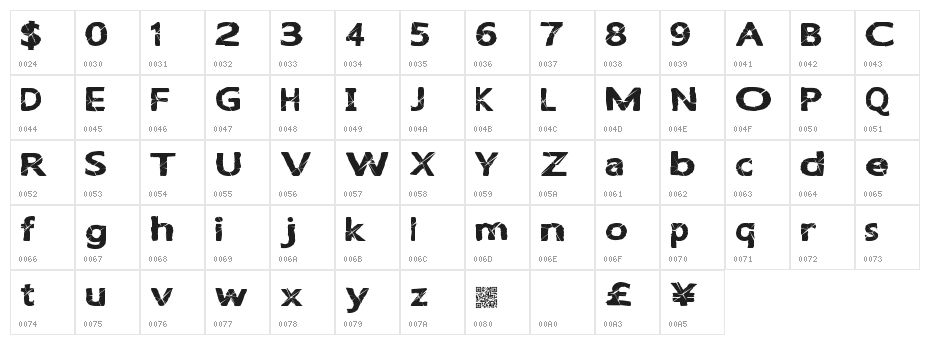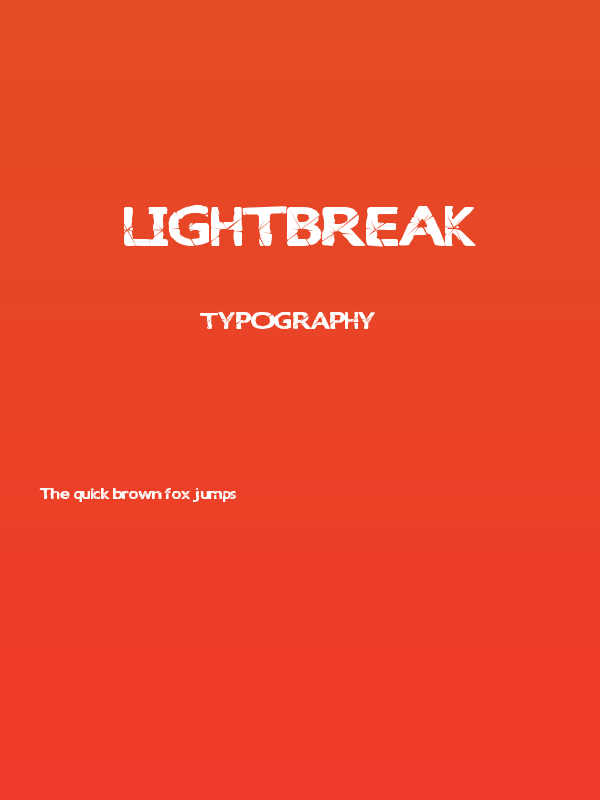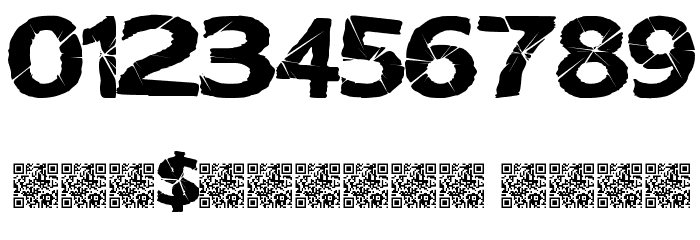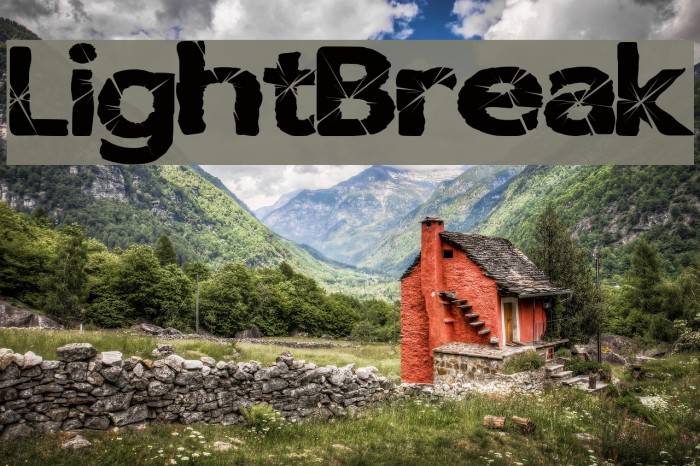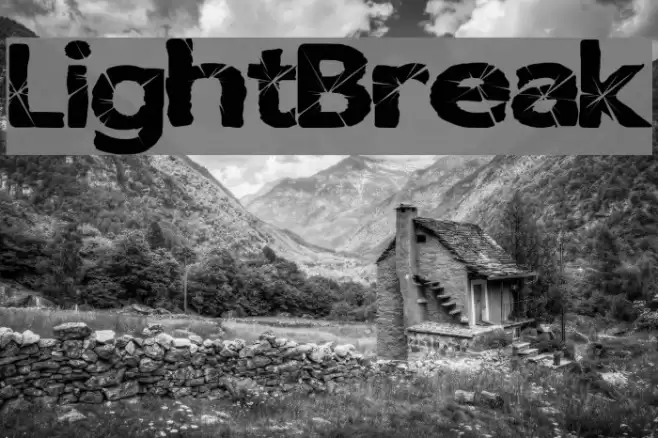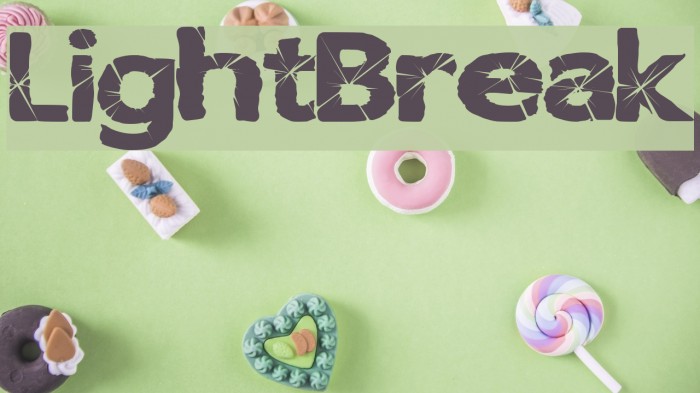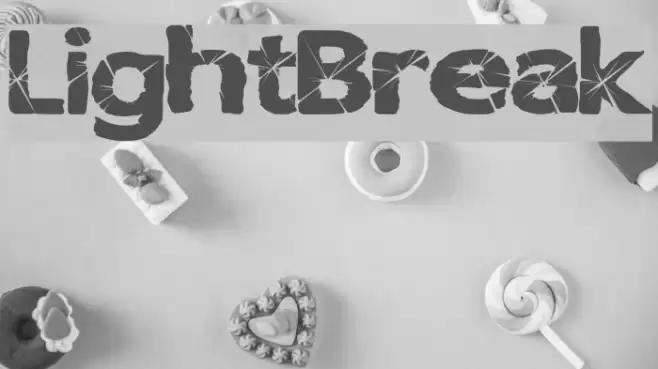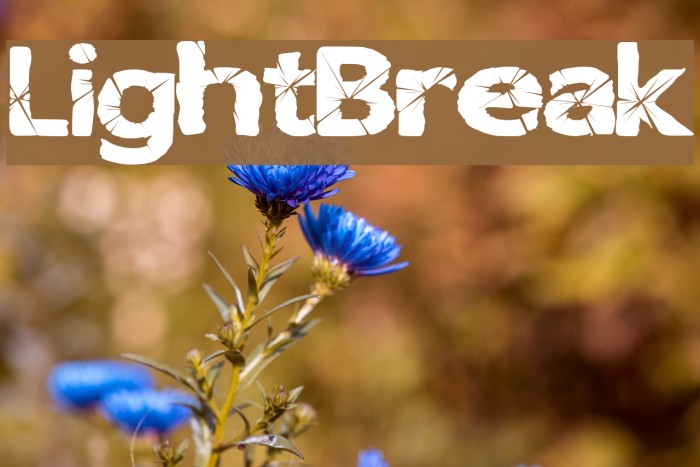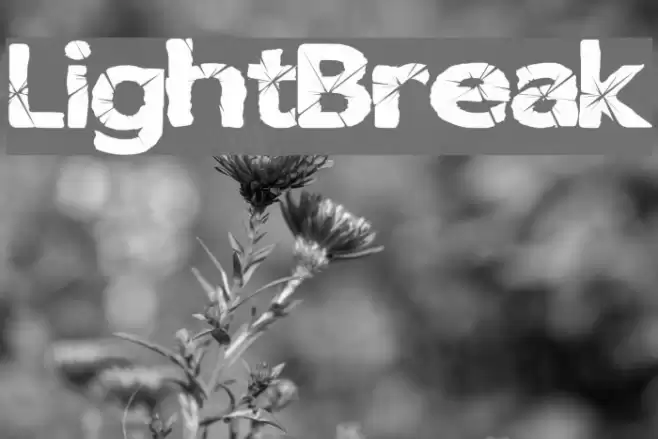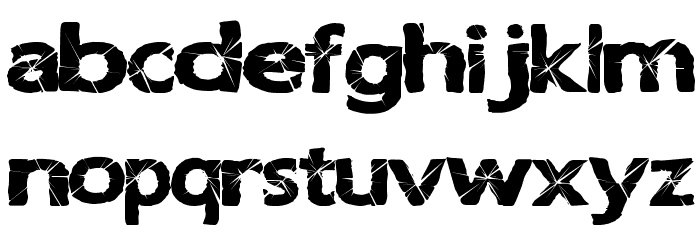
LightBreak Font
| कंट्रास्ट | High |
| समग्र शैली | Modern, Edgy |
| उपयोग का मामला | Headlines, Logos, Posters |
| सुझाए गए प्रोजेक्ट | Ideal for album covers, posters, branding for edgy or modern products, and any design needing a strong visual impact. |